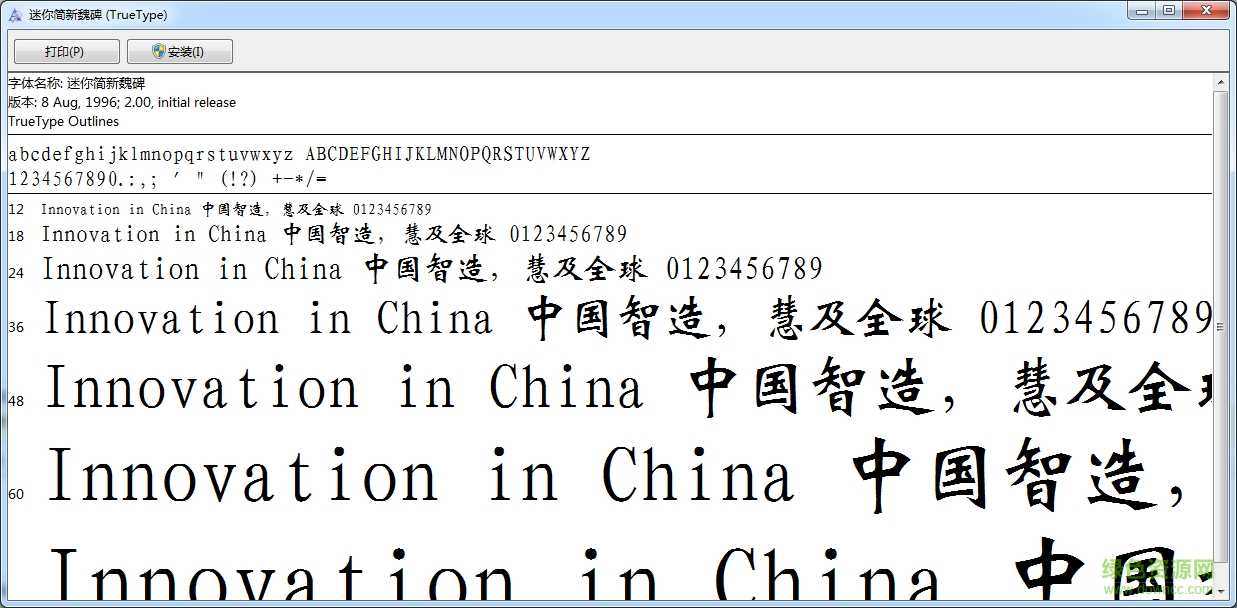
迷你簡新魏碑,是一款應(yīng)用于廣告創(chuàng)意設(shè)計方面的簡體中文字體,該字體以魏碑字為原形而設(shè)計,大方得體,整體效果更加出色,并且字庫完整,可以適用于名片設(shè)計、平面設(shè)計、廣告設(shè)計、報紙雜志、企業(yè)LOGO、商標注冊、電視臺廣告等領(lǐng)域!歡迎大家來綠色資源網(wǎng)下載使用。
1.字體采用了魏碑字為原型
2.字體看起來得格外大方得體
3.適合廣告設(shè)計、平面設(shè)計、印刷包裝、正文標題等人員使用